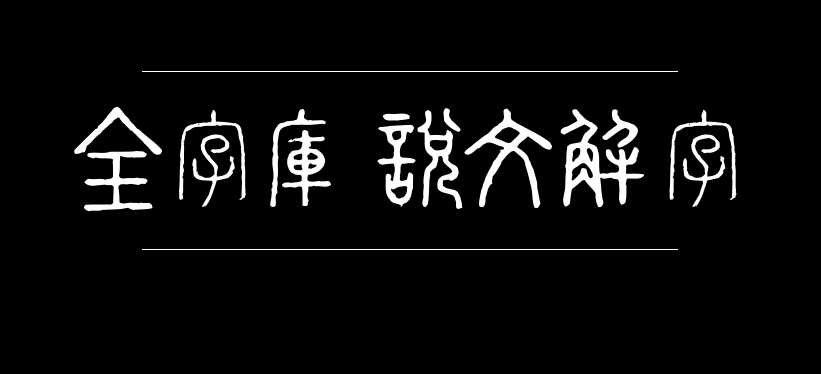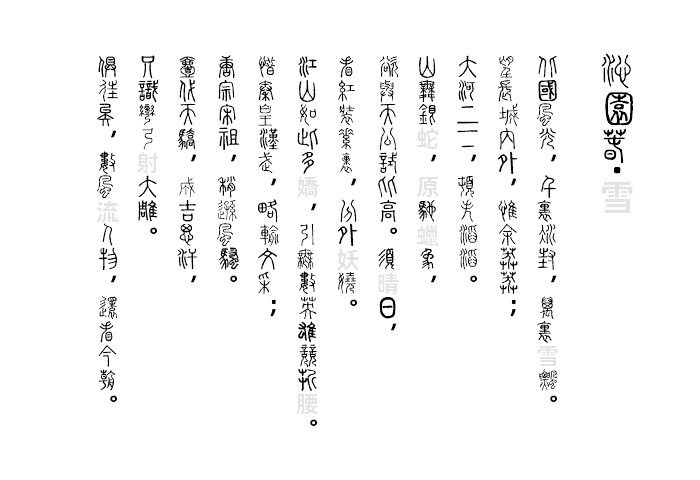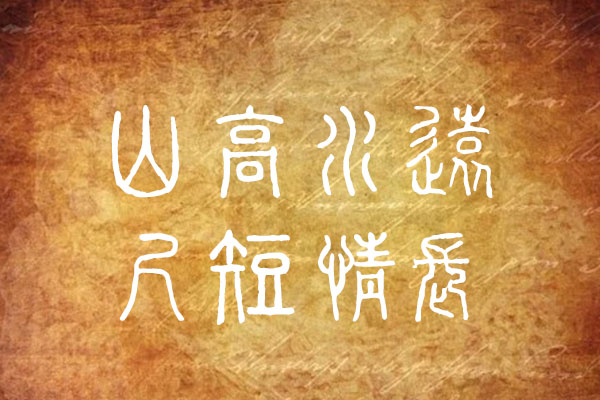
全字库说文解字
全字库说文解字是一款非常特别的中文字体,该字体为小篆风格,古色古香很有历史的味道。
《说文解字》是中国第一部系统地分析汉字字形和考究字源的字书,许慎著,成于安帝建光元年(121年)。原书十四篇,叙目一篇,正文以小篆为主,收9353字,又古文等异体同文1163字,解释十三万余字。
目前采用的版本为艺文印书馆所出版之《说文解字注》,后由南唐徐铉所校定,清代段王裁注之版本(世称大徐本)并参考黎明文化事业公司之《说文解字注》,及南唐徐铉所撰之《说文解字繁传》
由于说文解字原文与现行之Unicode编码并无一完整的对应,因此无法将所有的字形收录于本字体内。所以会有部分字码无法显示出正确的字形,使用的时候请多留意!目前收录于本字体内的字数共6721个字。